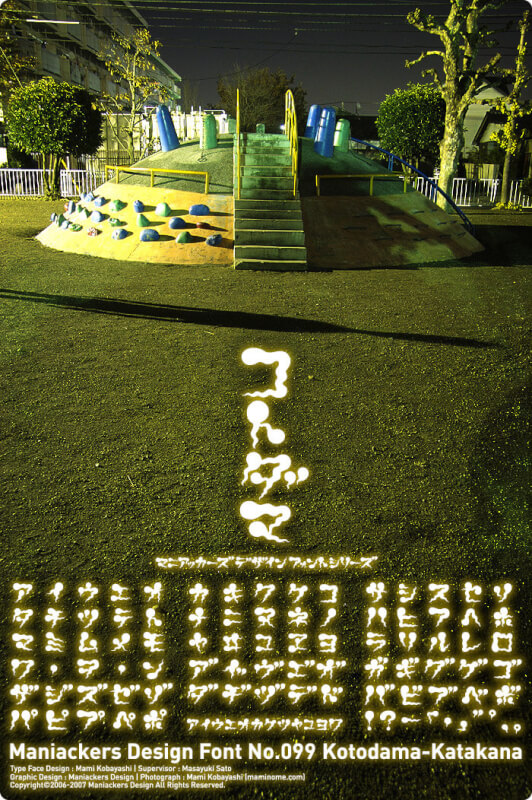
AlmostDead
死にかけ筆記体英字フォント。ダイイングメッセージなどの死にそうな人間が書いた文字をイメージしたデザインになっています。
AlmostDeadBloody font
死にかけ血滴る筆記体英字フォント。ダイイングメッセージなどの死にそうな人間が書いた文字をイメージしたデザインになっています。
Another call
ハロウィンで使えそうなカッコイイホラー系英字フォント。
Bloodyslime
ポップな流血英字フォント。ポップな太目の文字で流血風のしたたりがついたデザインになっています。
Double Feature
血が流れている太文字フォント。
g_コミックホラー
マンガのネーム用として、ホラーや恐怖、恐喝、悪人等の恐ろしげなセリフの表現として使えるフォント。縦書きにも対応。
g_コミック古印体
楷書風・隷書風・行書風の字画が混在している、古印体的な手書きフォント。
g_コミック古印体nocutかな
g_コミック古印体をもとに切り込み部分を削除し、線をなめらかにしたフォント。
GhostParty
西洋風ゴーストをイメージした英字フォント。
Nemukeフォント!
怖い話にはもってこいのネバネバしたフォント。
No.013
文字の太さを変えることにより不気味さを表現したフォント。
Solstice Of Suffering
白抜きの文字から流血したようなデザインフォント。
TheNeighbors
不気味な顔の英字フォント。
イバラ字
字形も雰囲気も尖った感じのフォント。
オバケ
形はクネクネと先太、中細で、血のような滴りがついているホラーフォント。
コトダマ-KT
イメージとしての『魂』のカタチがユラユラ揺らめいているような線で構成されているフォント。ドロドロ~、ユラユラ~っとしたデザインにオススメです。
しらなみ
スラッとした印象のフォント。今にも消えてしまうようなイメージです。